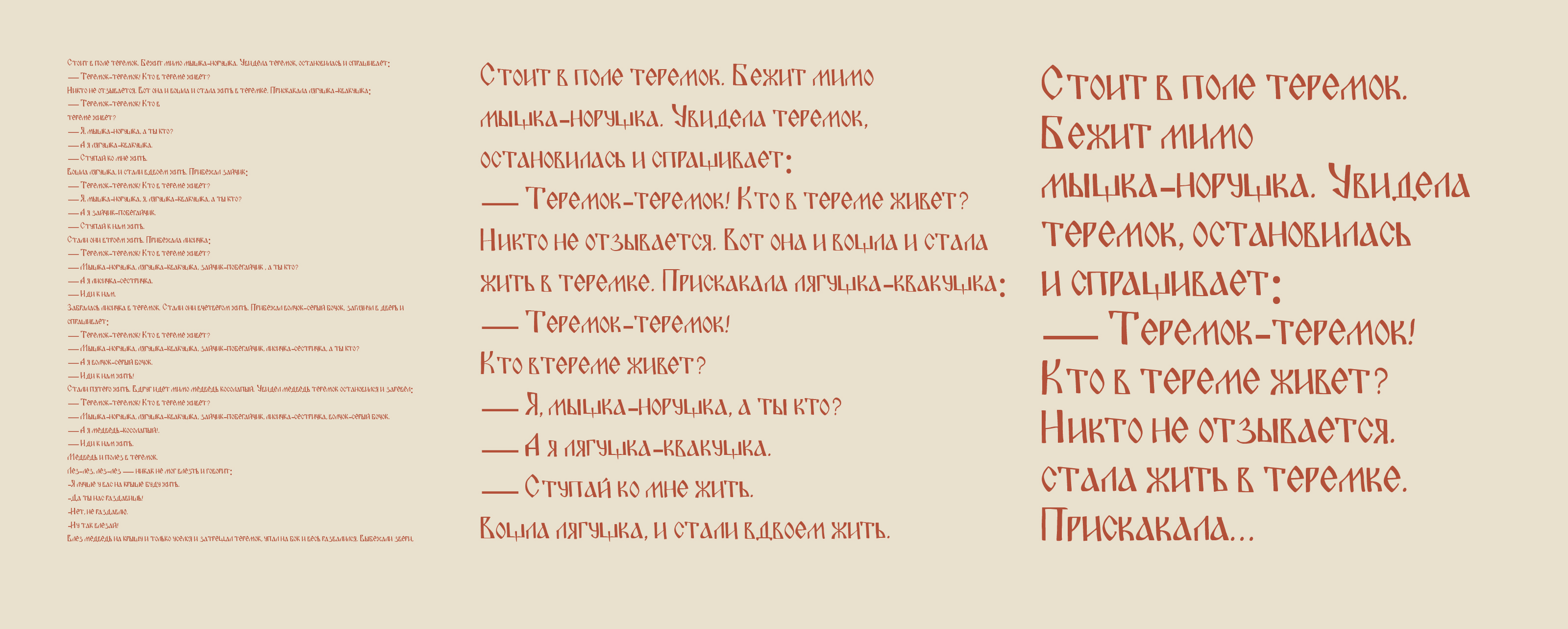
Бабкины страсти – это шрифт на основе старого устава, в современной интерпретации. Изначально буквы были отрисованы на бумаге с помощью пера, а затем, перенесены в программу. Каждая буква как из старинной рукописи, наполнена духом русских традиций.
Отлично подойдет для исторических проектов, брендинга и искусства.